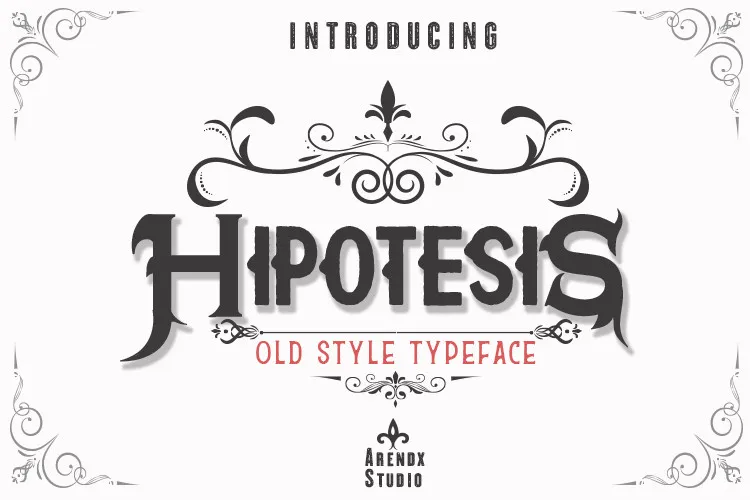
Hipotesis Old Style Typeface – Fonte Grátis
Hipotesis Old Style Typeface
Descubra a Hidromanta Antiga Estilo Hipótese, uma elegante tipografia gótica perfeita para reviver os clássicos dos anos 1900. Desenvolvida pelo designer arendxstudio, esta fonte é ideal para aqueles que buscam um estilo singular e sofisticado. Com linhas leves e detalhes cuidadosamente projetados, a Hidromanta Antiga Estilo Hipótese oferece uma experiência visual impecável em qualquer projeto. Especialmente adequada para aplicações digitais ou impressas, esta fonte garante um resultado sofisticado e arrojado. Não perca essa oportunidade de trazer vida aos seus designs com o talento da arendxstudio. Se desejar contribuir para a manutenção desta fonte única, qualquer doação é muito apreciada.